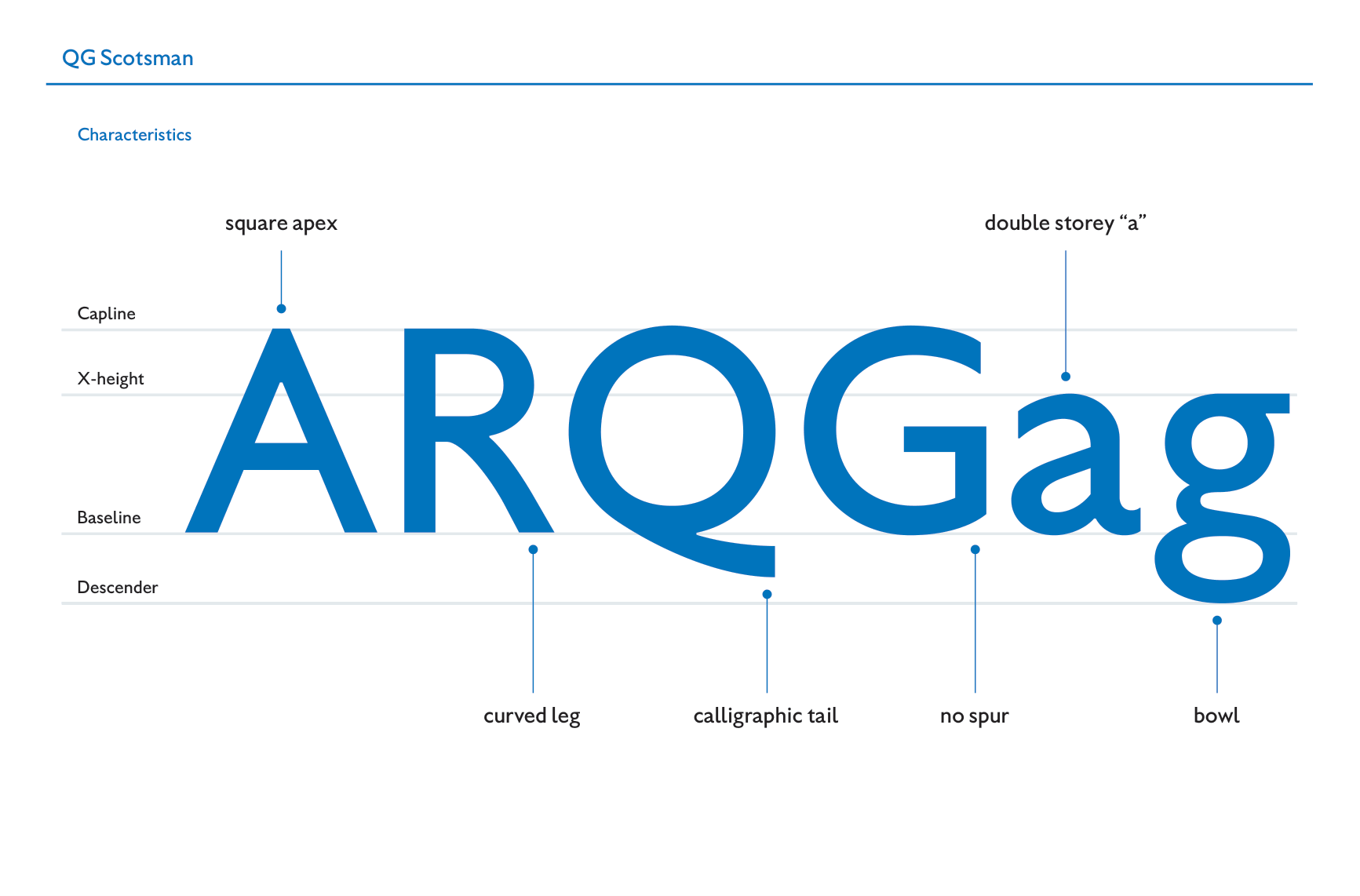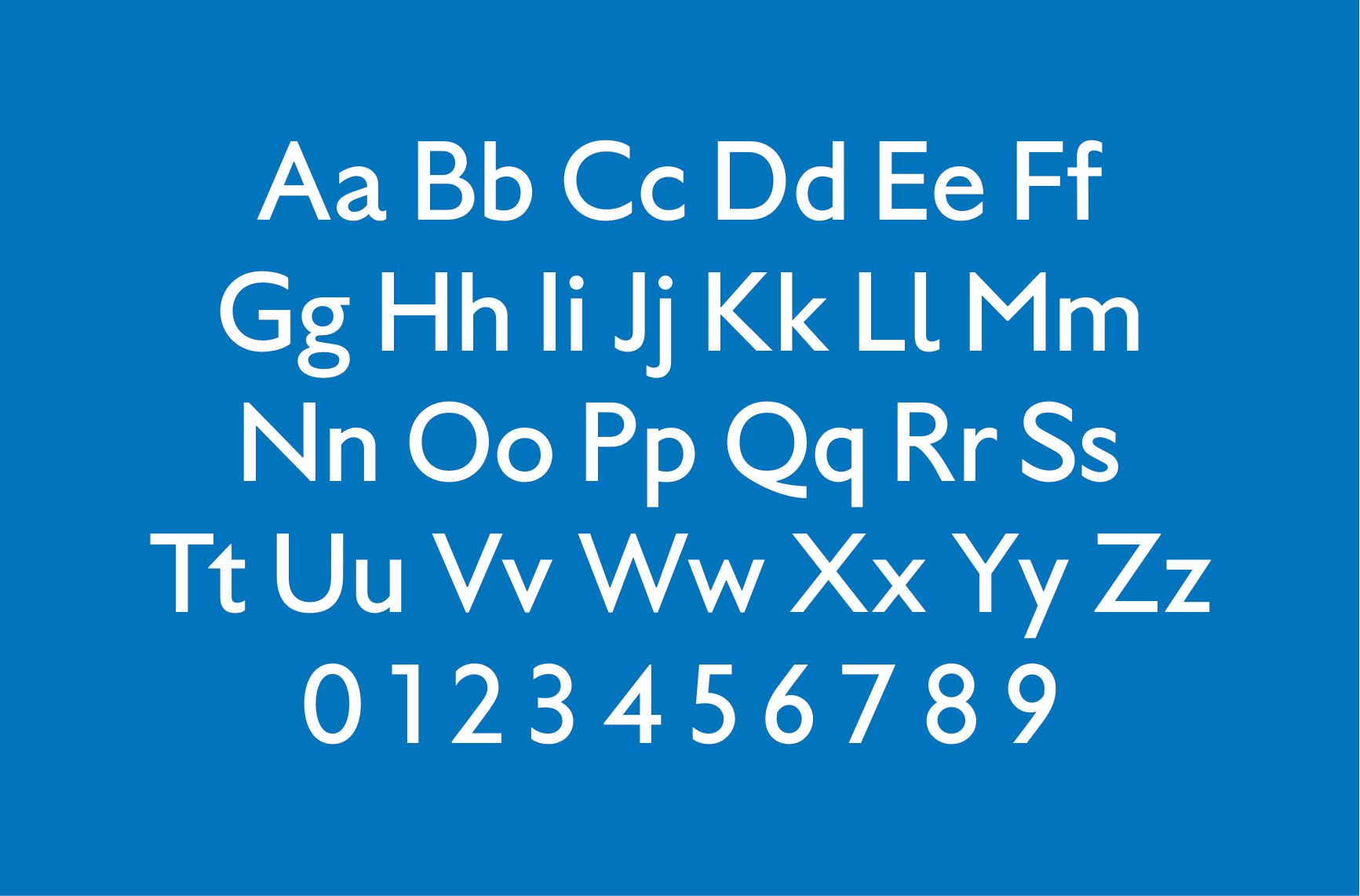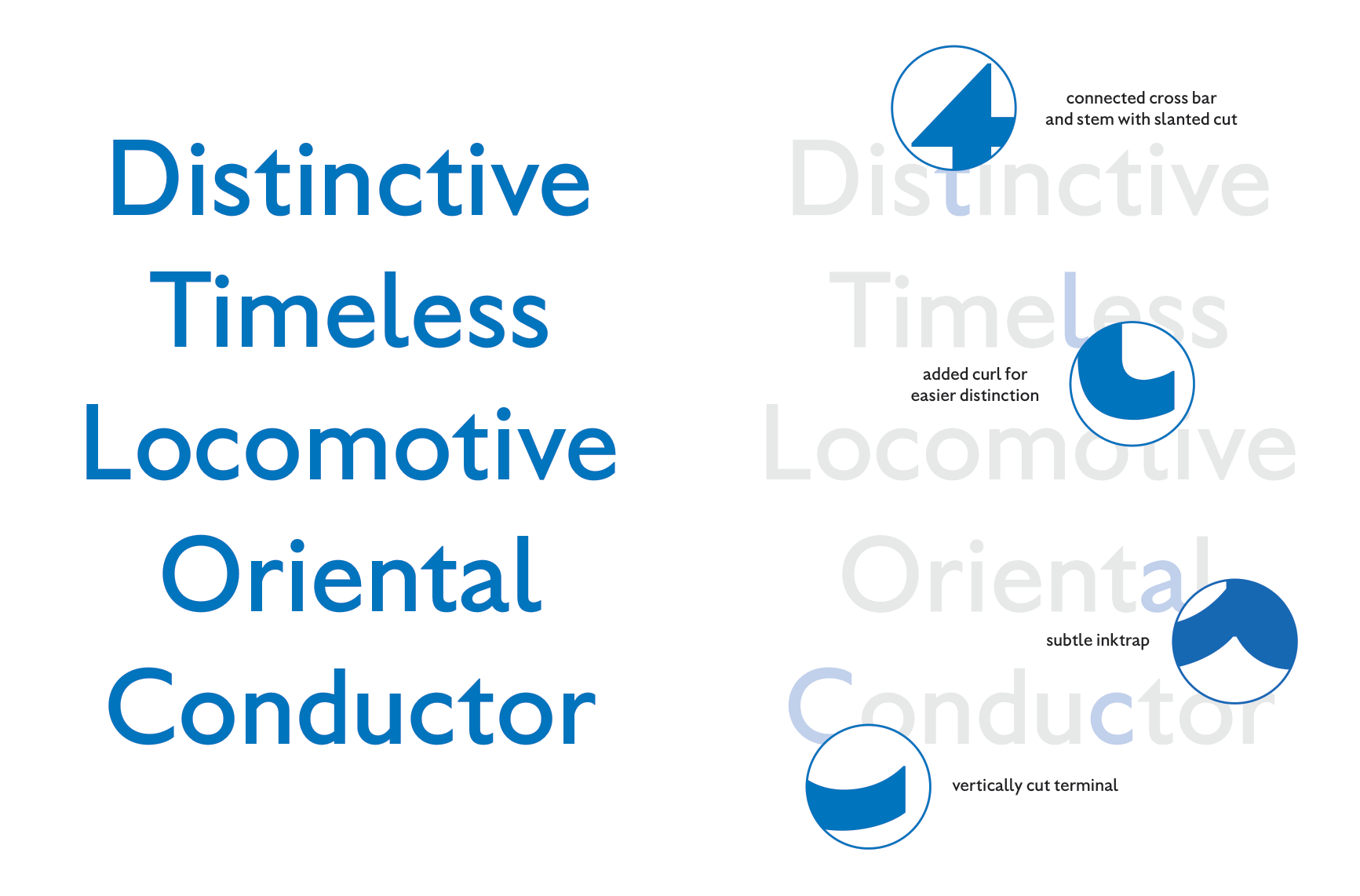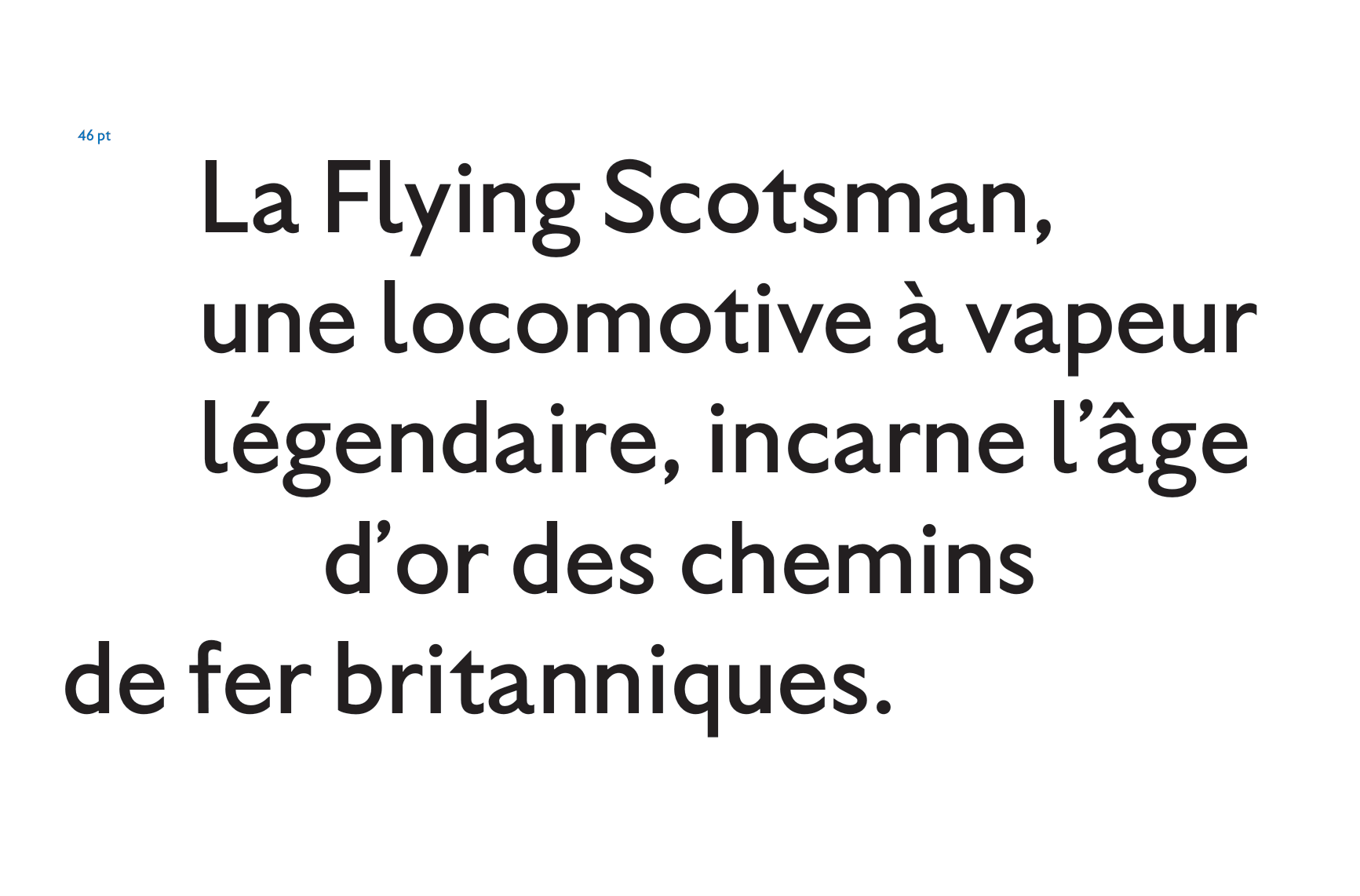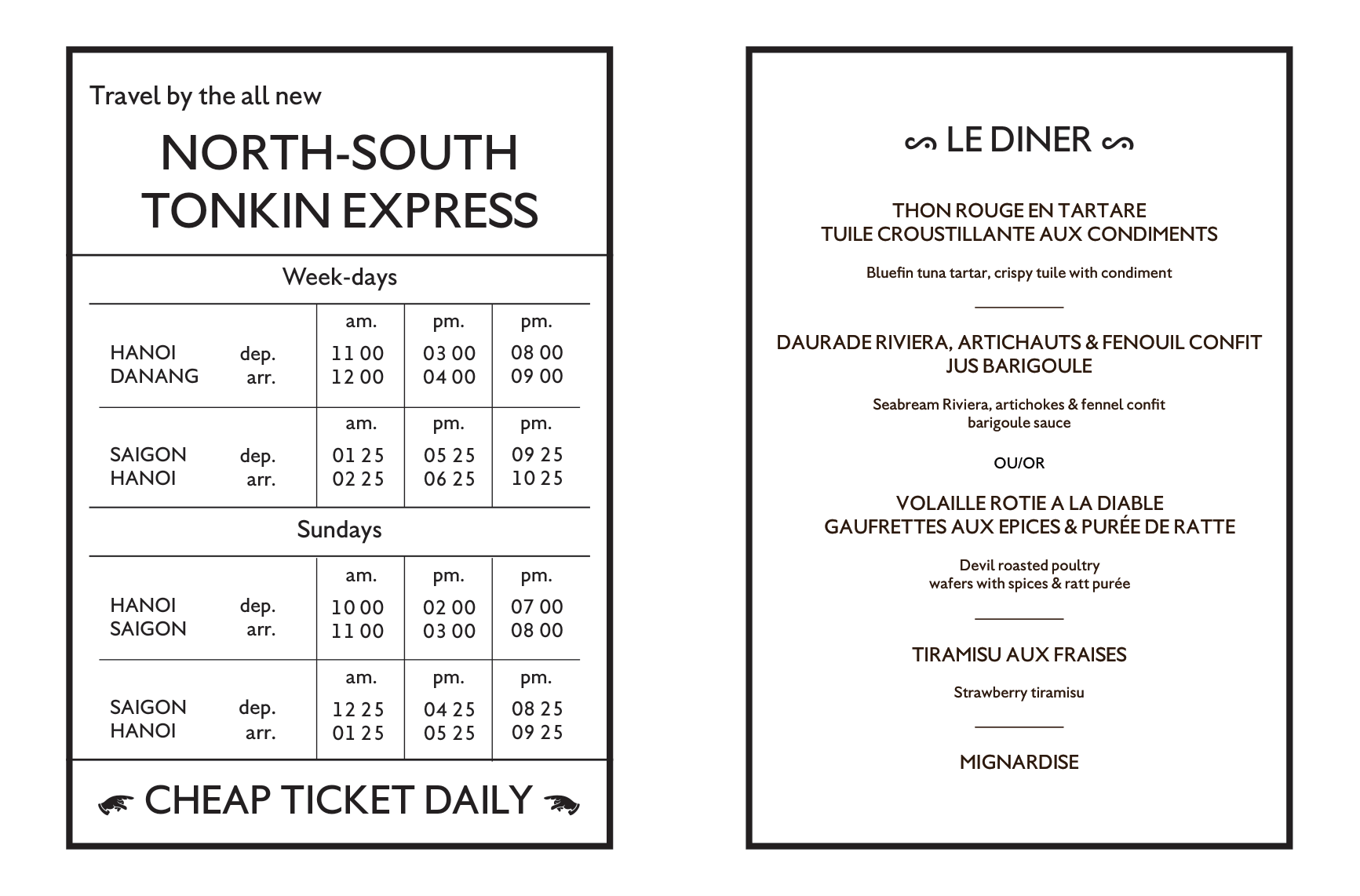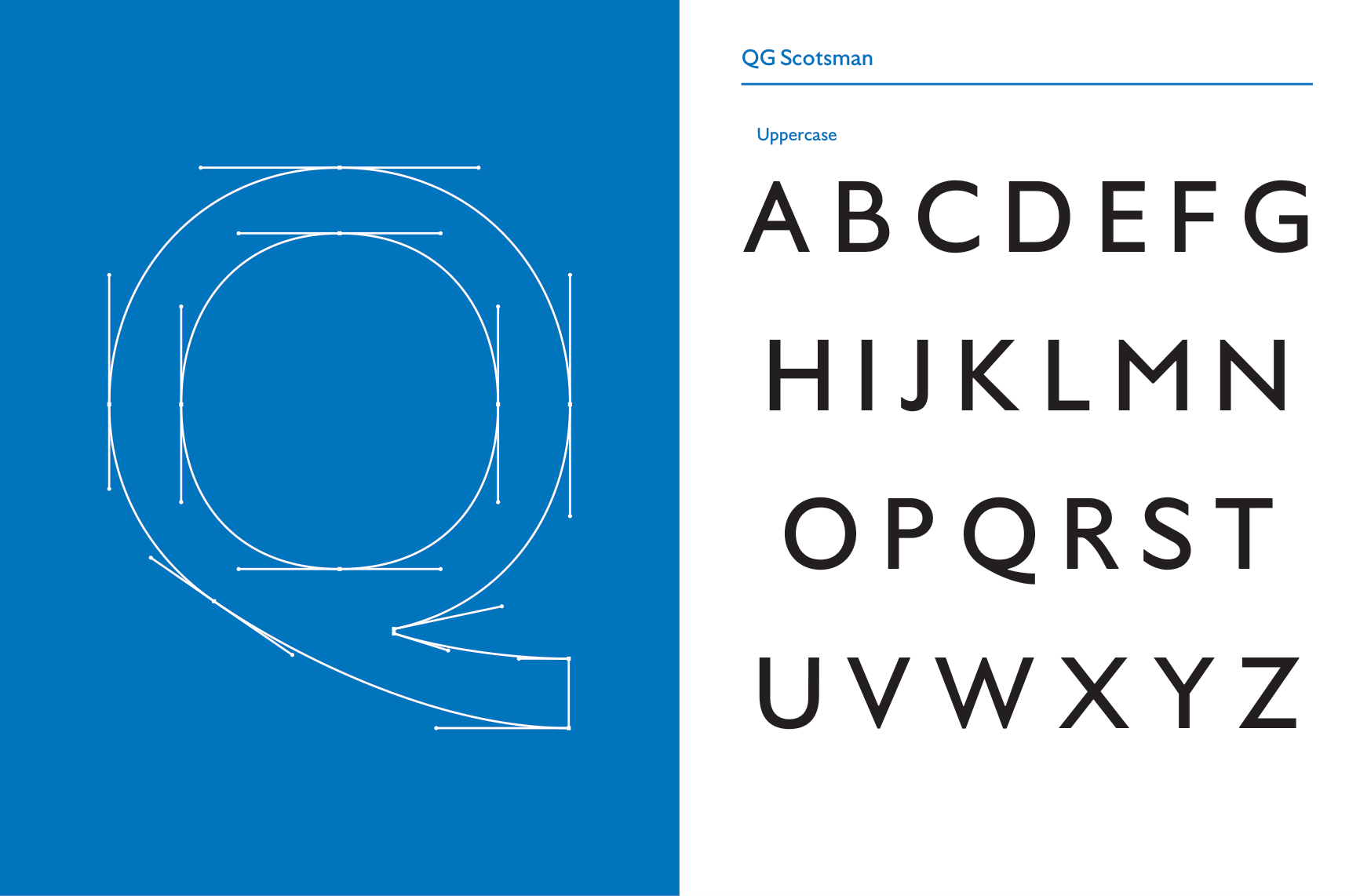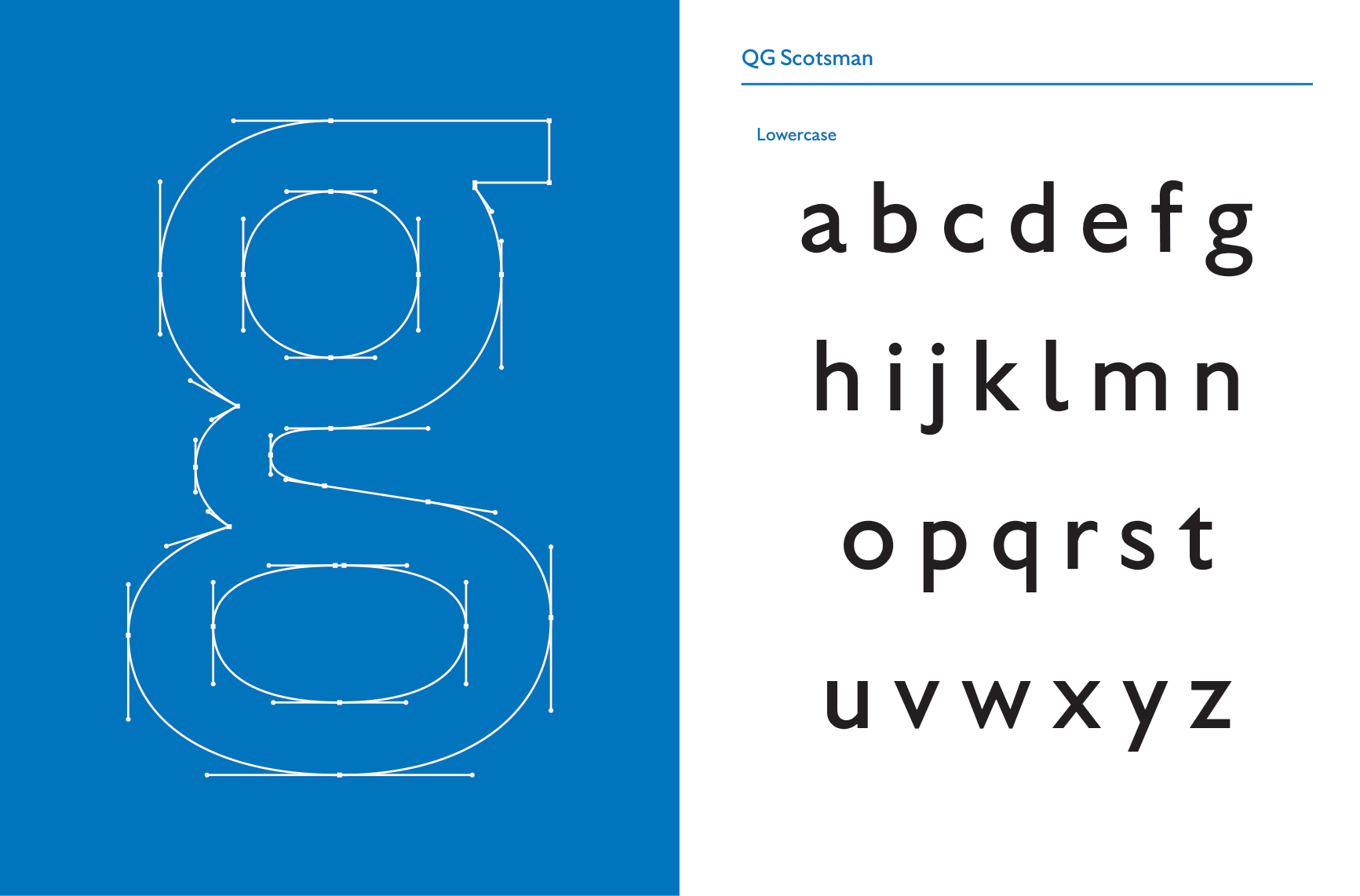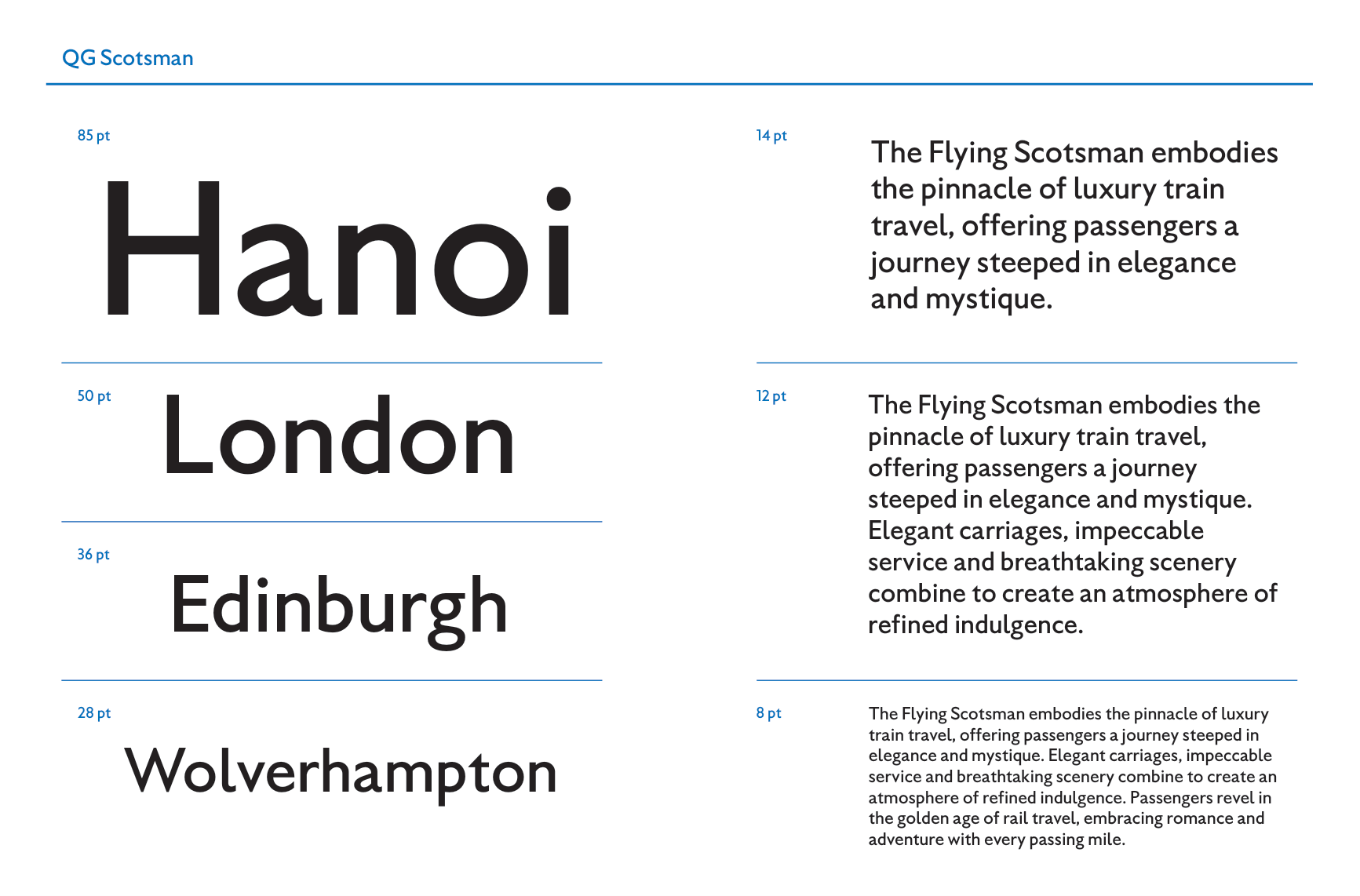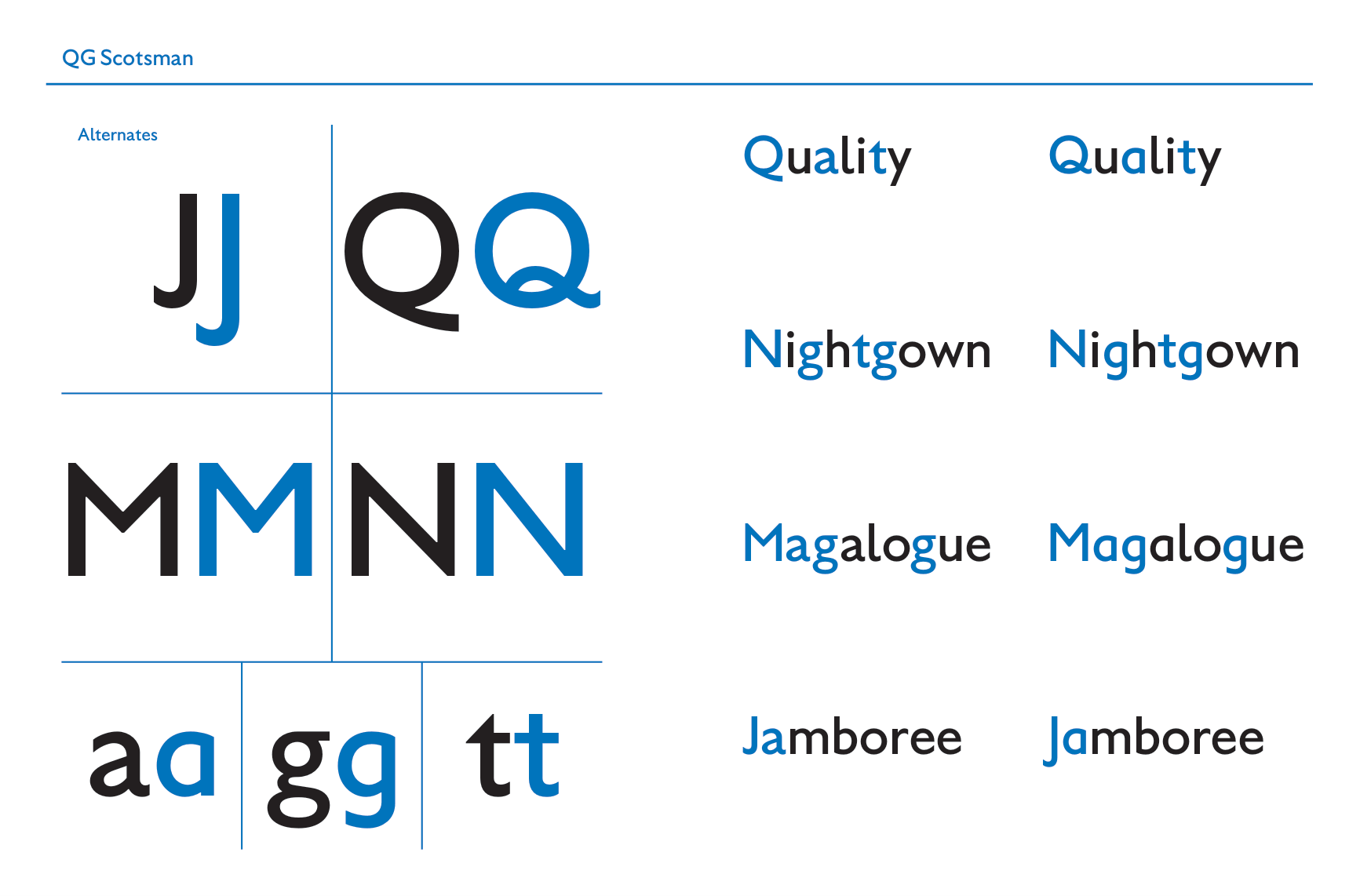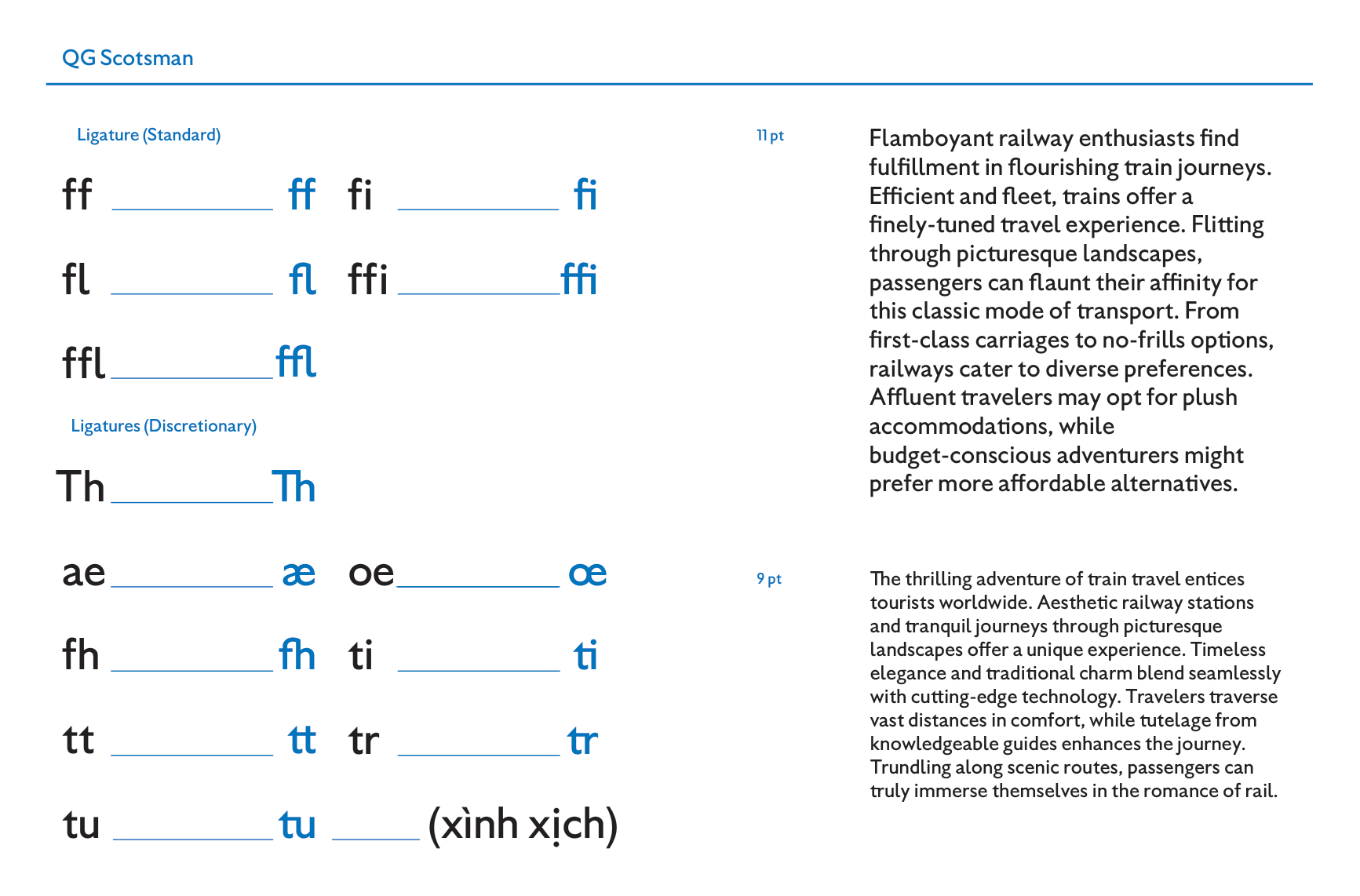
Scotsman
Về Scotsman: QG Scotsman là một bản phục dựng của Gill Sans. Nó gần với bản mẫu gốc năm 1928 hơn so với bản phục dựng kỹ thuật số chính thức của Monotype vào năm 2015. Được thiết kế để sử dụng cho cả tiêu đề (display) và đôi khi cho văn bản dài (body text), kiểu chữ này mang cảm giác thân thiện, dễ đọc, đồng thời tích hợp các tính năng OpenType để tăng thêm tính linh hoạt và cá tính.
Humanist Sans-serif
Text
Scotsman
Railway
Scotsman
Đường sắt
Scotsman
Distinctive Shapes
Scotsman
Người lữ hành
Scotsman
Gill Sans is a humanist sans-serif typeface, and one of the most popular fonts from Monotype.
Scotsman
Designed by Eric Gill in 1926, and launched in 1928, it was developed with intention to be a competitor to a wave of German geometric sans-serif families in the market at the time. The typeface was met with great success, with its first commercial publication use from the London and North Eastern Railway (LNER) and later on, British Railway. Dubbed as “the British Helvetica”, it quickly became a monument in British design, influenced many other typefaces of the same genre.